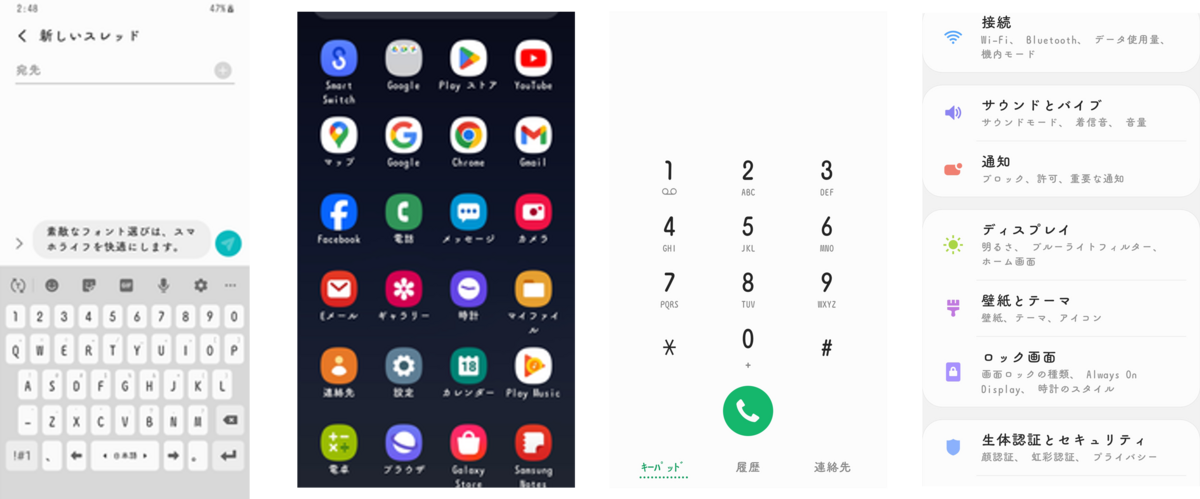
フォントワークスがサムスンのモバイルデバイスをパーソナライズできるモバイルフォント「FlipFont」に38書体を提供
フォントワークスはサムスンのモバイルデバイスをパーソナライズできるモバイルフォント「FlipFont」に書体を提供している。
「もじと もっと じゆうに」をタグラインに掲げ、多くの人に気軽にフォントを楽しんでもらえることを目指すフォントワークスでは、このタグラインのもと、フォント着せ替えサービスFlipFont(フリップフォント)を搭載したGalaxyスマートフォンにフォントワークス日本語フォントの提供を開始し、現在までに全38書体が揃ったことを2024年3月29日に発表した。
フォントワークスのフラッグシップフォントの筑紫書体シリーズや人気のデザイン書体パルシリーズ、読みやすさ・見やすさ・文字の美しさを備えたUDフォントなど豊富なラインナップを提供している。
今後も随時書体を追加していく予定で、気分に合わせたフォントの着せ替えや自分らしさ溢れるフォントセレクトを楽しむことができる。
▼筑紫ANA丸ゴS B
▼パルラムネ
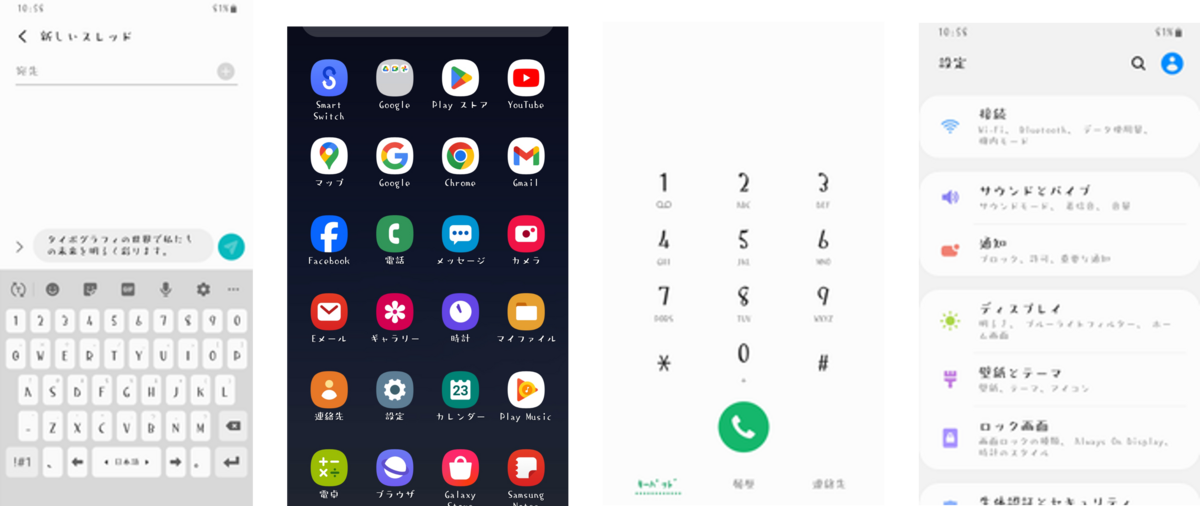
▼コミックミステリ
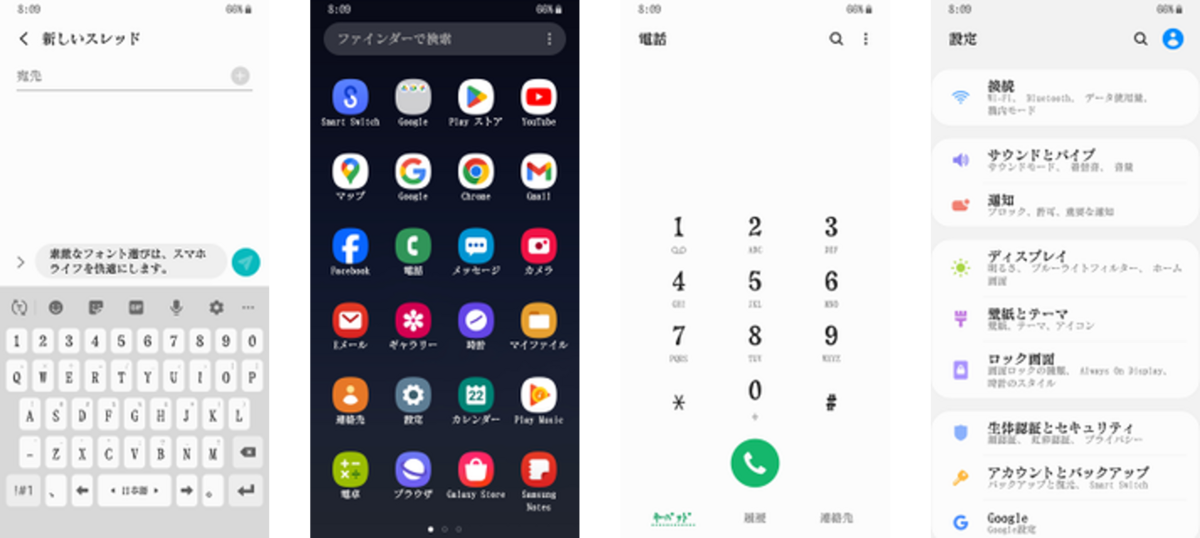
▼UD角ゴラージL DB
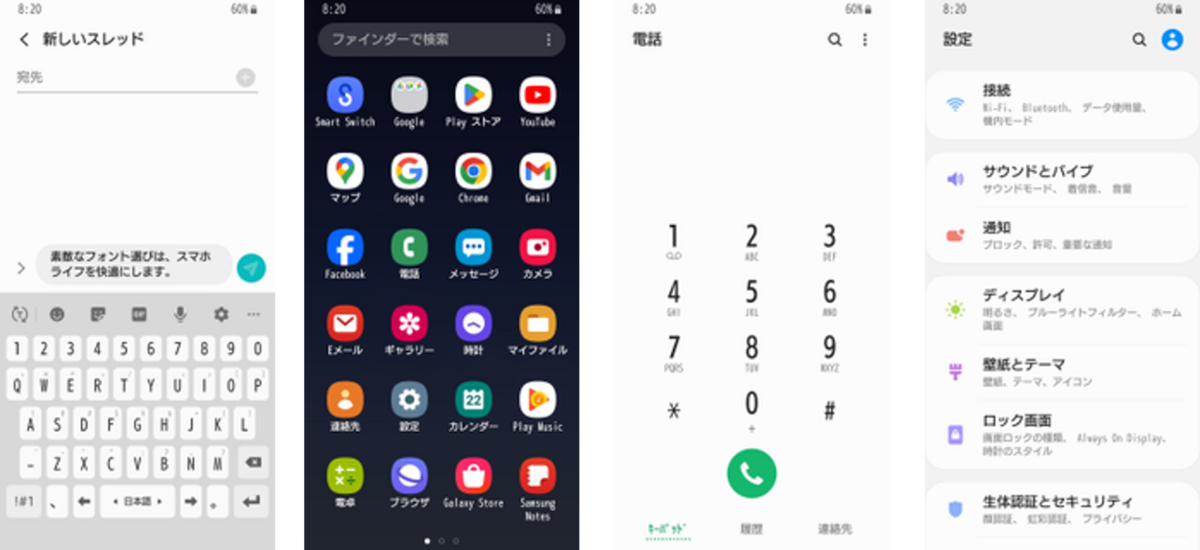
▼現在提供している書体は以下の通り。